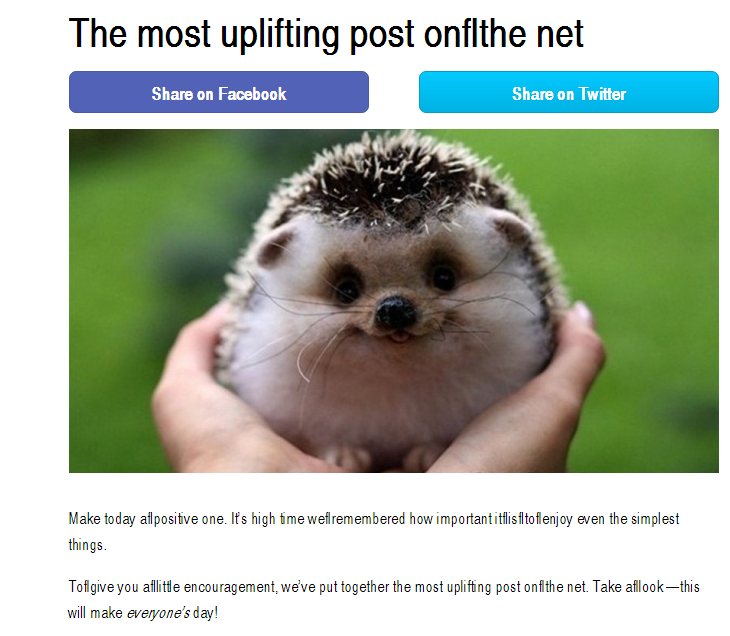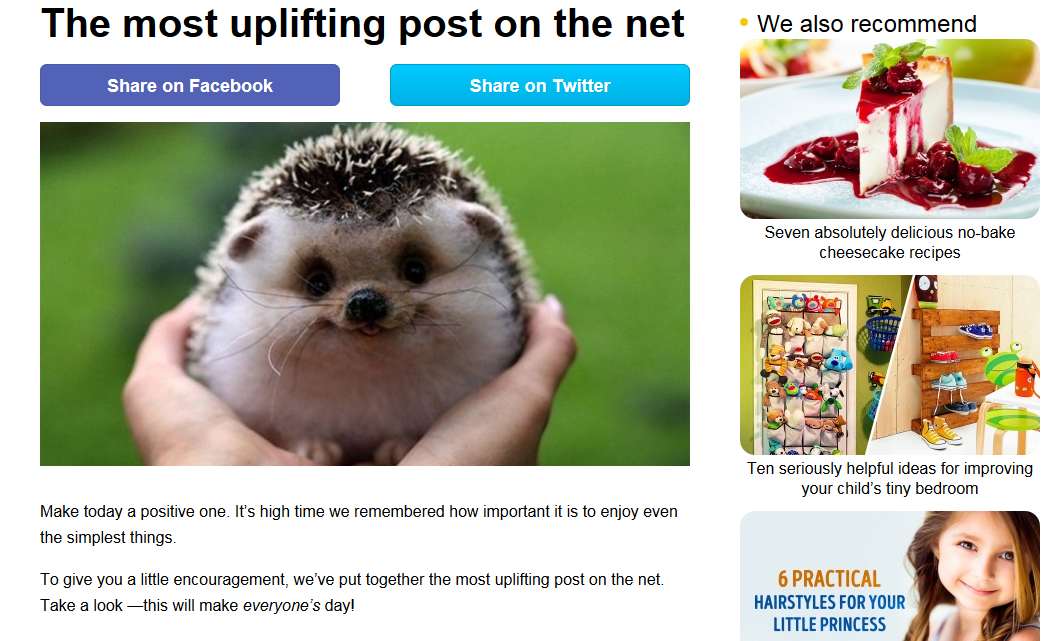
Ủa, sao Chrome lại "nghịch" vậy trời? Hiện tượng lạ là khi vào một số trang web trên Chrome ở laptop, khoảng trống giữa các từ cứ bị dính mấy ký hiệu "fl" lởm vào, nhìn rất khó chịu luôn á. Trong khi đó qua bên Firefox thì lại xịn sò, mượt mà, không bị gì cả. Chữ thì nhỏ, hẹp, đọc muốn nhức mắt